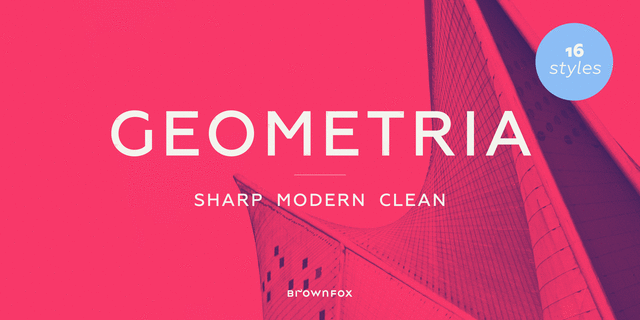
Шрифт Геометрия отличается от своих родственников необычным сочетанием динамичных и статичных свойств, что создаёт ощущение подвижности и уверенности одновременно. Слегка завышенная талия у прописных придаёт им изюминку. В то время как верхний регистр отсылает к «американской» стилистике и старым гротескам 19 века, строчные явно тяготеют к ренессансным формам. Геометрия — шрифт с чистыми контурами и равномерным, «серебристым» набором, но при этом не скучный: в нём есть оттенок кокетливости и дружелюбности. За простыми формами скрываются порой противоположные черты. Шрифт иногда строг, иногда игрив; порой нетороплив, порой динамичен; может быть жёстким, может быть изящным; остросовременным и немного винтажным. Умелые руки типографа смогут выявить и подчеркнуть в нём ту грань, которую требует решение поставленной задачи.
В состав шрифта входят несколько комплектов цифр и знаков валют, альтернативные глифы, множество лигатур и знаки пунктуации для двух регистров. 815 символов в каждом начертании и богатый диапазон насыщенностей расширяют возможности типографа и открывают поле для творческих поисков. Мы желаем вам вдохновенной работы!
Дизайнеры Вячеслав Кириленко и Гаянэ Багдасарян, 2013.